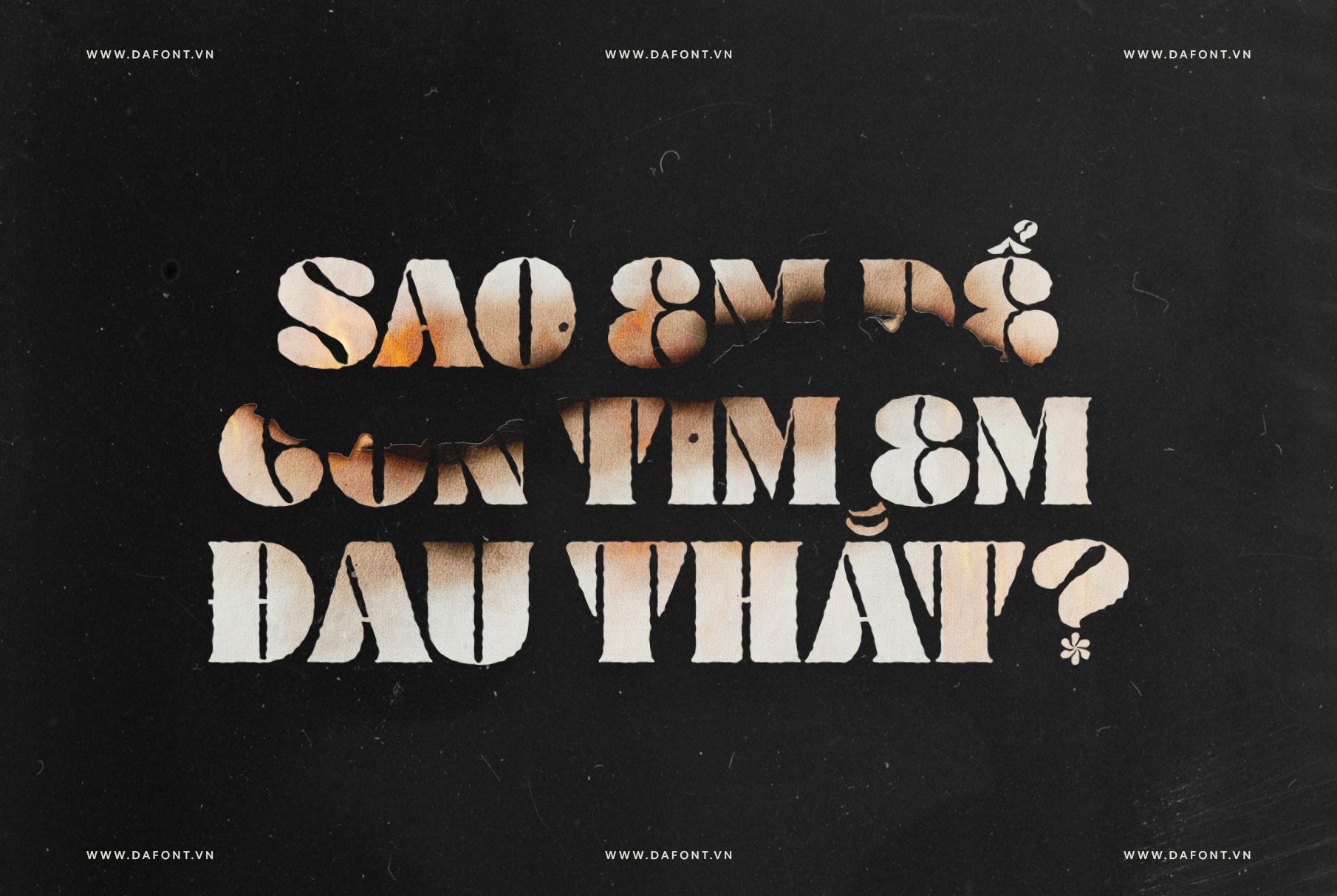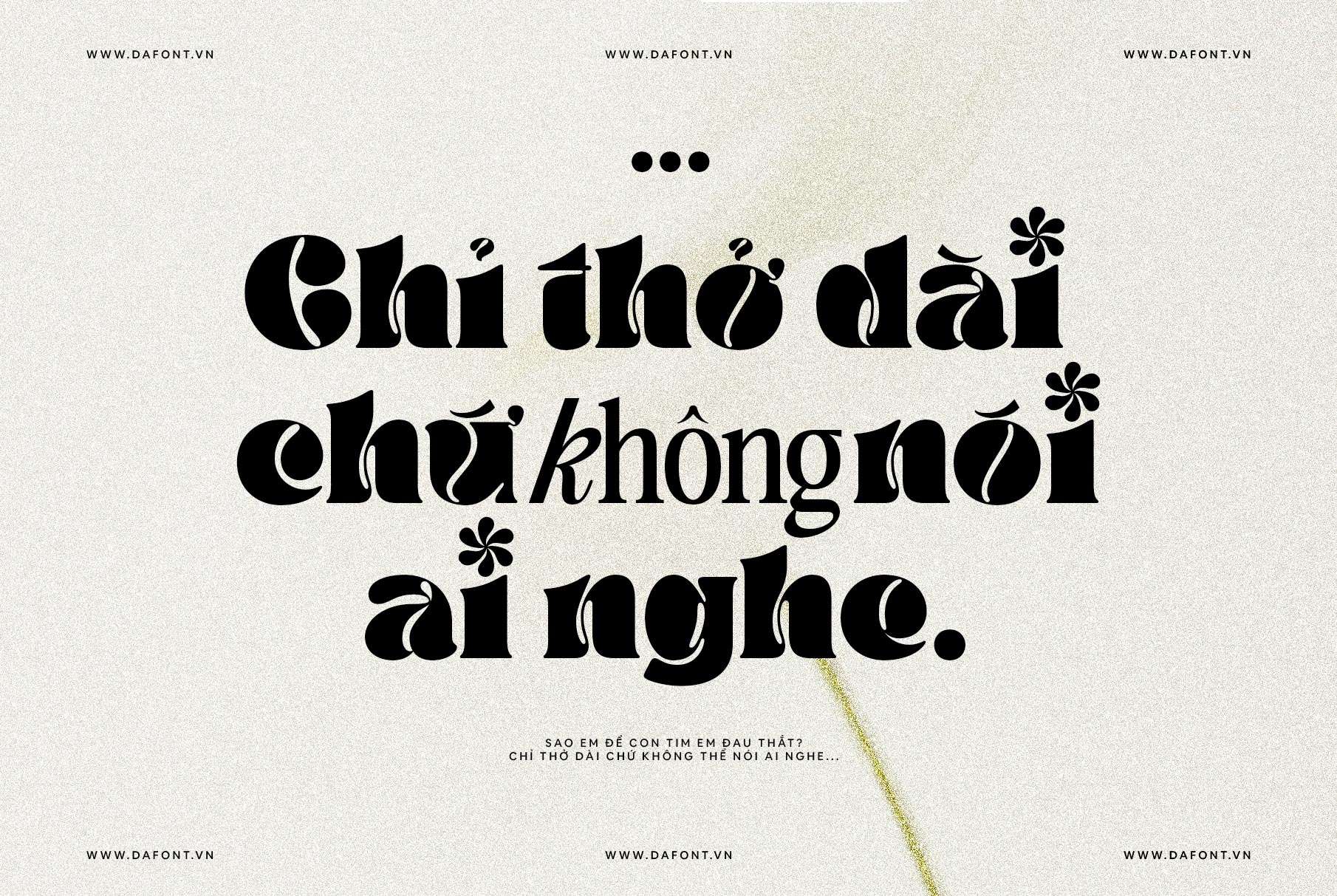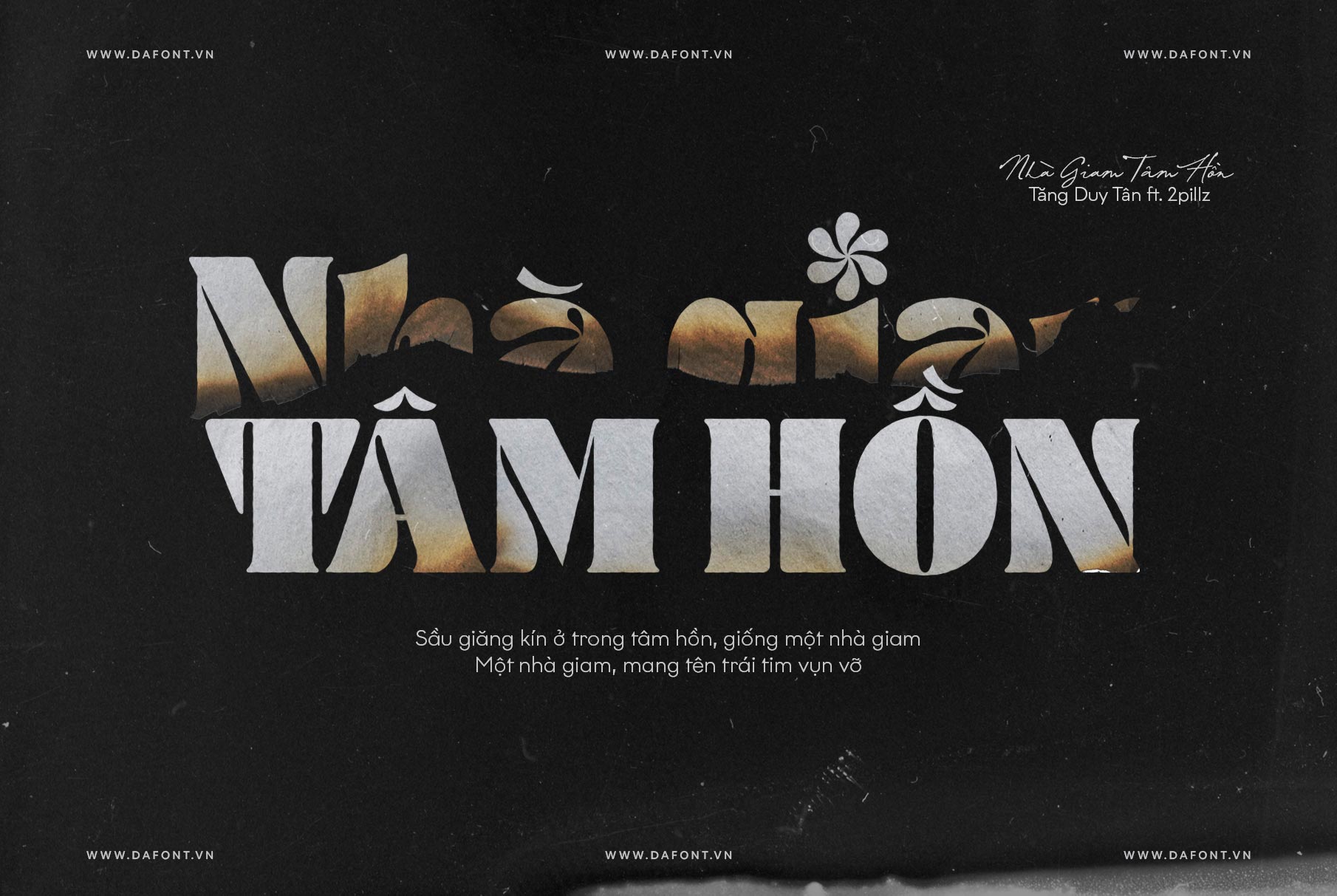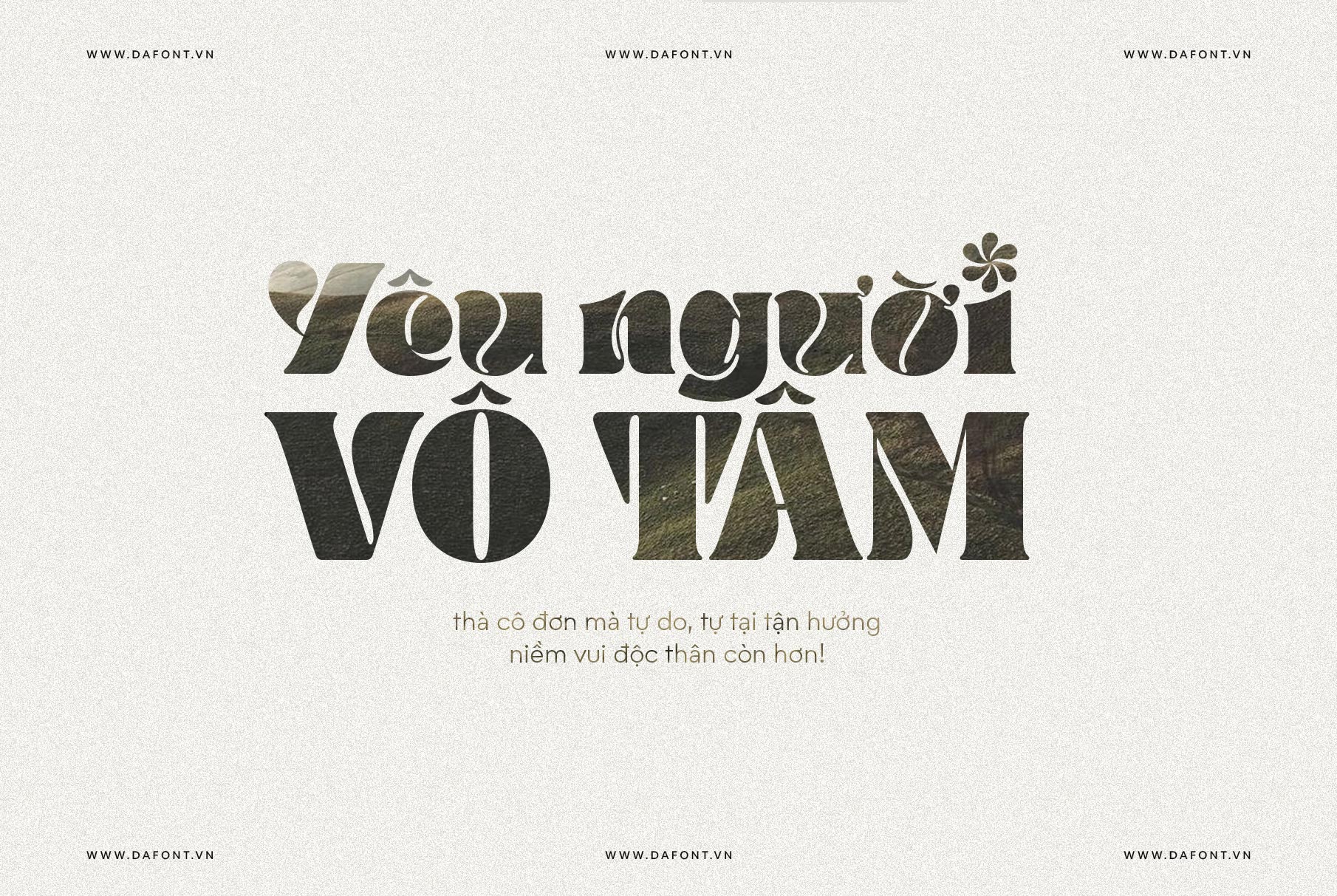
TAN – DAISY font là một kiểu chữ hiển thị (display typeface). Đây là font chữ được yêu thích nhờ vào nét độc đáo, trẻ trung và đầy sức sống. TAN – DAISY mang đến phong cách thiết kế nổi bật và cá tính, phù hợp cho nhiều dự án sáng tạo.
Với nét đậm và quirky, font này mang đậm phong cách hoài cổ, nhưng vẫn không kém phần hiện đại dễ dàng thu hút ánh nhìn, giúp bạn tạo ra những thiết kế đầy cuốn hút và tràn đầy cá tính từ poster, logo đến các bài đăng trên mạng xã hội.Hãy thử TAN – DAISY và cảm nhận sức mạnh của sự phá cách!
Đặc điểm nổi bật của TAN – DAISY
Điều khiến TAN DAISY font trở nên khác biệt chính là phong cách retro pha trộn với chút gì đó tinh nghịch, vui tươi. Được thiết kế với đường nét dày và đậm, TAN DAISY không chỉ dễ đọc mà còn giúp tăng sức hút cho các thiết kế. Đây là font lý tưởng cho các ấn phẩm quảng cáo, tiêu đề lớn, poster và cả các thiết kế thời trang, làm nổi bật nội dung một cách ấn tượng.
Phong cách retro quirky của TAN – DAISY
Với thiết kế quirky và groovy, TAN – DAISY font mang lại cảm giác hoài cổ nhưng không kém phần hiện đại, phù hợp với xu hướng thiết kế retro đang lên ngôi. Sự pha trộn giữa các nét uốn lượn và đường nét dày làm cho kiểu chữ này trở nên lạ mắt và thú vị. TAN – DAISY không chỉ là một font chữ, mà còn là công cụ tạo cảm hứng, giúp thiết kế của bạn trở nên thu hút và độc đáo.
Ứng dụng của TAN – DAISY trong thiết kế
Nếu bạn đang tìm kiếm một font chữ nổi bật để thu hút sự chú ý, TAN – DAISY chính là lựa chọn lý tưởng. Nhờ vào đặc trưng đậm và mạnh mẽ, kiểu chữ này phù hợp cho:
- Poster quảng cáo: Giúp truyền tải thông điệp mạnh mẽ, dễ nhìn thấy từ xa.
- Logo và nhận diện thương hiệu: Tạo ấn tượng thị giác độc đáo.
- Bao bì sản phẩm: Đặc biệt là các sản phẩm hoài cổ, có phong cách vintage hoặc trẻ trung.
- Mạng xã hội: Font này có thể dùng để tạo ra các bài đăng, story nổi bật.
Lý do bạn nên chọn TAN – DAISY
TAN DAISY font không chỉ là kiểu chữ hiển thị mà còn là phong cách. Sự pha trộn giữa nét hoài cổ và thiết kế vui tươi giúp TAN-DAISY dễ dàng thu hút người xem. Với TAN – DAISY, các nhà thiết kế có thể thoải mái sáng tạo, làm cho nội dung trở nên mới mẻ, sinh động và cuốn hút hơn bao giờ hết.
Đặc biệt Font TAN – DAISY được việt hóa rất kỹ các ký tự và dấu được chỉnh sửa lại, kerning đầy đủ và tối ưu hóa để sử dụng dễ dàng trên bất kỳ phần mềm hoặc ứng dụng thiết kế nào.